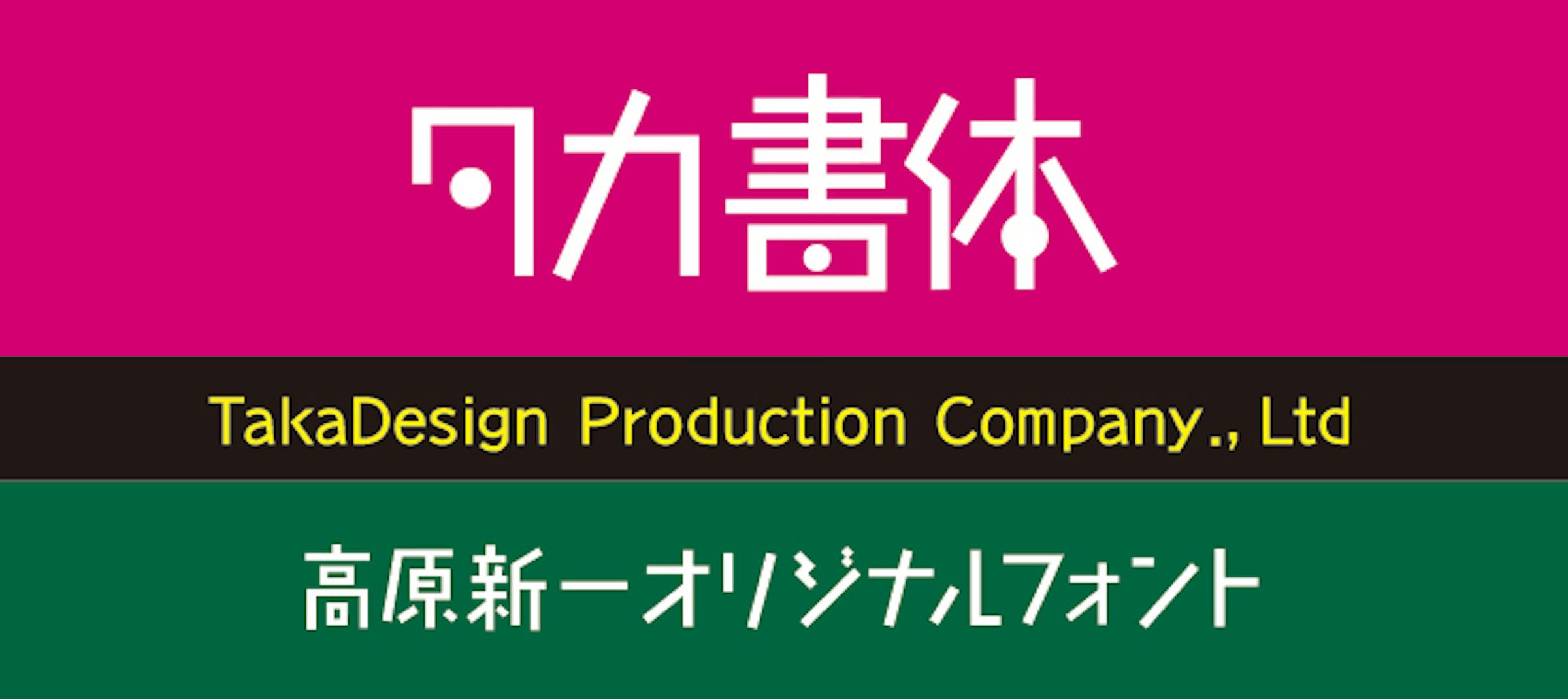
フォントテクノロジー大手のMonotypeが、日本のタイプファウンダリー「たかデザインプロダクション」との提携を発表した。この提携により、定額制フォントサービス「フォントワークス LETS」と「FONTPLUS」に15書体が新たに追加される。
たかデザインプロダクションは、日本のタイポグラフィ分野で独自の地位を確立しているタイプファウンダリーだ。同社の書体は、伝統的な日本文字の美しさと現代的なデザインセンスを融合させた作品として評価が高い。今回の提携により、これらの高品質な書体が定額制サービスを通じて幅広いユーザーに提供されることになる。
フォントワークス LETSは、年間定額制でフォントを利用できるサービスとして、多くのデザイナーや企業に利用されている。FONTPLUSも同様に、Web上でフォントを利 用できるサービスとして人気を集めている。両サービスともに、たかデザインプロダクションの15書体を追加することで、ユーザーの選択肢がさらに拡大する。
この動きは、日本のタイポグラフィ業界におけるフォントアクセシビリティの向上という観点から重要な意味を持つ。定額制サービスの普及により、高品質な書体を使用するためのコストが削減され、より多くのクリエイターが質の高いタイポグラフィを実現できるようになる。
Monotypeは今回の提携を通じて、日本市場での存在感を強化するとともに、世界的なフォントサービス拡充の一環として位置付けている。たかデザインプロダクションの独創的な書体デザインが、国際的なフォントコミュニティにもたらす影響は大きいと期待される。